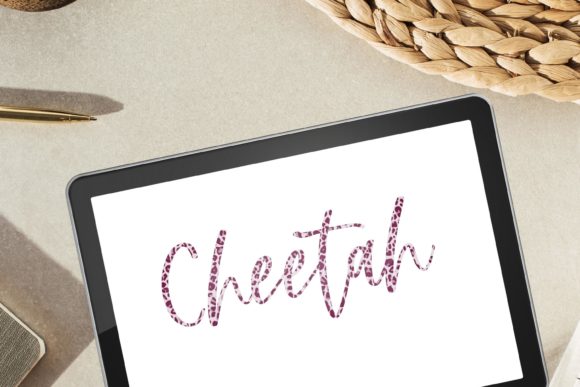
Cheetah Procreate Lettering Brush
Jika anda sedang mencari aset berkualiti tinggi seperti Cheetah Procreate Lettering Brush, pakej premium ini merupakan pilihan yang hebat untuk projek kreatif anda.
Dicipta dengan ketepatan, Cheetah Procreate Lettering Brush menyediakan vektor yang bersih, tipografi yang licin dan lesen komersial untuk ketenangan fikiran.
Sama ada anda mencipta produk POD (Print on Demand), jemputan perkahwinan atau grafik media sosial, Cheetah Procreate Lettering Brush amat bersesuaian.